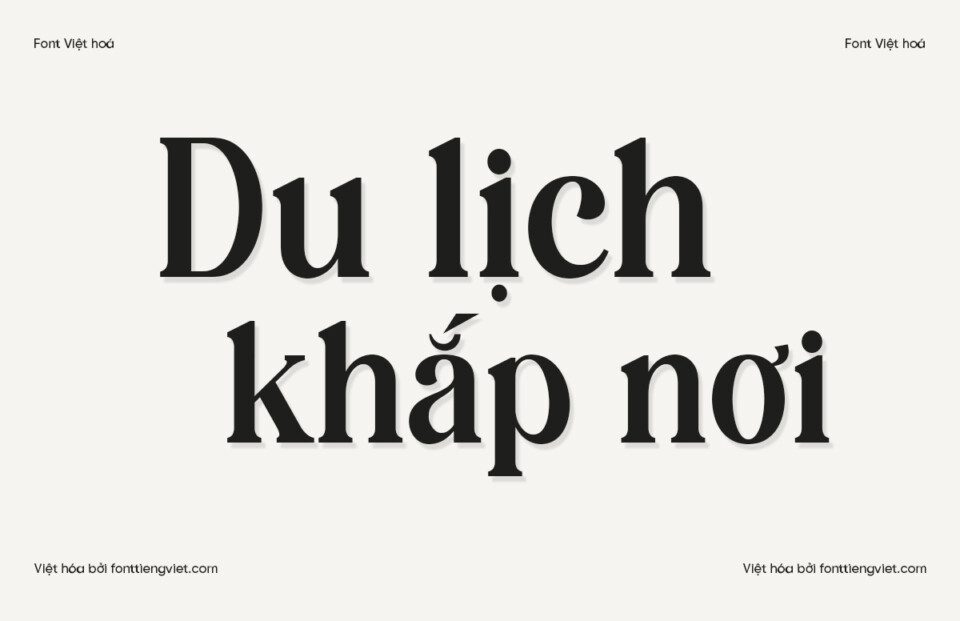
Font Việt hóa 1FTV VIP Bugalo
Font Việt hóa 1FTV VIP Bugalo: Bộ Font Chữ Nghệ Thuật Độc Đáo Cho Thiết Kế Việt
Giới thiệu về Font Việt hóa 1FTV VIP Bugalo
Trong thế giới thiết kế đồ họa hiện đại, việc lựa chọn một Font Miễn Phí chất lượng luôn là ưu tiên hàng đầu của các bạn học sinh và giáo viên. Font Việt hóa 1FTV VIP Bugalo nổi lên như một lựa chọn hoàn hảo nhờ sự kết hợp tinh tế giữa phong cách cổ điển và hơi thở đương đại. Đây là bộ font được tinh chỉnh kỹ lưỡng về dấu tiếng Việt, giúp người dùng không còn lo lắng về lỗi hiển thị khi soạn thảo văn bản hay thiết kế ấn phẩm trường học. Với các đường nét bo tròn mềm mại nhưng vẫn giữ được sự chắc chắn, bộ chữ này mang lại cảm giác thân thiện và gần gũi, rất phù hợp cho các dự án sáng tạo đòi hỏi tính thẩm mỹ cao.
Đặc điểm nổi bật của Font Việt hóa 1FTV VIP Bugalo
Thiết kế tối ưu cho ngôn ngữ tiếng Việt
Điểm mạnh nhất của Font Việt hóa 1FTV VIP Bugalo chính là hệ thống dấu câu được sắp xếp cân đối. Trong tiếng Việt, các dấu như huyền, sắc, hỏi, ngã, nặng thường dễ bị chồng chéo nếu font chữ không được tối ưu. Tuy nhiên, phiên bản 1FTV VIP Bugalo đã giải quyết triệt để vấn đề này, đảm bảo mỗi ký tự đều rõ ràng và dễ đọc. Điều này cực kỳ quan trọng đối với các bài thuyết trình giảng dạy hoặc các tập san của học sinh, nơi mà sự rõ ràng của thông tin luôn được đặt lên hàng đầu.
Tính ứng dụng đa dạng trong môi trường giáo dục
Không chỉ dừng lại ở việc soạn thảo, Font Việt hóa 1FTV VIP Bugalo còn rất đa năng trong việc trang trí. Bạn có thể sử dụng bộ font này để làm tiêu đề bài báo tường, thiết kế thiệp chúc mừng thầy cô hoặc làm nổi bật các khẩu hiệu trong lớp học. Sự linh hoạt của nó cho phép người dùng biến hóa từ phong cách tinh nghịch, vui nhộn đến trang trọng, lịch sự chỉ bằng cách thay đổi kích thước và màu sắc. Điều này giúp kích thích khả năng sáng tạo của các bạn học sinh trong quá trình học tập và làm việc nhóm.
Cách sử dụng Font Việt hóa 1FTV VIP Bugalo hiệu quả
Phối hợp màu sắc và bố cục
Để Font Việt hóa 1FTV VIP Bugalo phát huy hết vẻ đẹp, người dùng nên chú ý đến độ tương phản màu sắc. Với các nét chữ dày và rõ, bạn nên chọn những gam màu tươi sáng trên nền tối hoặc ngược lại để tạo điểm nhấn thị giác. Trong các tài liệu học tập, việc sử dụng font này cho các tiêu đề chính sẽ giúp học sinh dễ dàng theo dõi mạch nội dung của bài giảng. Ngoài ra, việc kết hợp với các hình ảnh minh họa sinh động sẽ tạo nên một tổng thể hài hòa và chuyên nghiệp.
Kết luận về bộ Font Việt hóa 1FTV VIP Bugalo
Có thể khẳng định rằng, Font Việt hóa 1FTV VIP Bugalo là một công cụ không thể thiếu trong kho tài nguyên của những người yêu thích thiết kế tại Việt Nam. Sự chỉn chu trong từng nét chữ và tính ứng dụng cao đã khiến bộ font này trở thành người bạn đồng hành tin cậy cho cả giáo viên và học sinh. Nếu bạn đang tìm kiếm một giải pháp để làm mới các ấn phẩm của mình, hãy truy cập Font Miễn Phí, Font Việt Hóa, Font Việt hóa 1FTV VIP Bugalo để trải nghiệm ngay sự khác biệt mà bộ chữ này mang lại cho không gian sáng tạo của bạn.